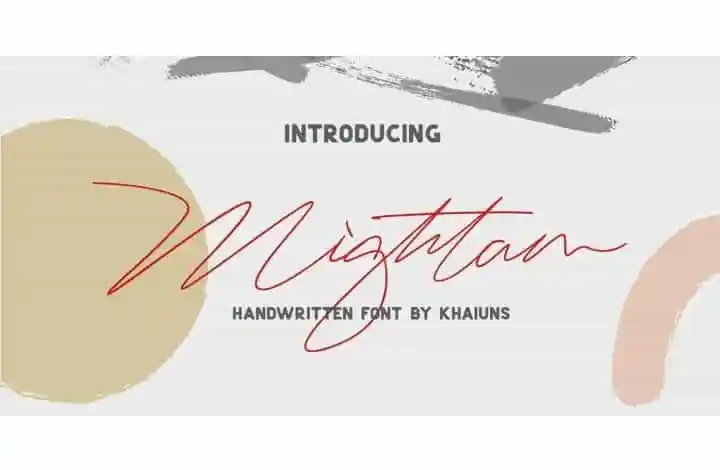
Mightam Handwritten Font – Download Grátis
A fonte Mightam Handwritten é uma elegante escolha para designers buscando adicionar um toque de personalidade a seus projetos visuais. Essa fonte monoline, com terminações suaves e 82 ligaturas fluidas, foi criada por Khaiuns da plataforma 99designs. O resultado é uma fonte que combina a modernidade do design gráfico com o encanto da calligrafia tradicional. Perfumada para uso em logotipos, selos, embalagens, headlines, outdoors, camisetas e aparelhos, cartões de agradecimento ou convites para casamento, Mightam é uma escolha incrível. Suas formas fluidas tornam-a ideal para criar mensagens encantadoras e atrativas. Em resumo, essa fonte é um ótimo exemplo do encontro entre design gráfico contemporâneo e estilo clássico da calligrafia. Com Mightam Font, você pode alcançar a perfeição em seu próximo projeto visual!